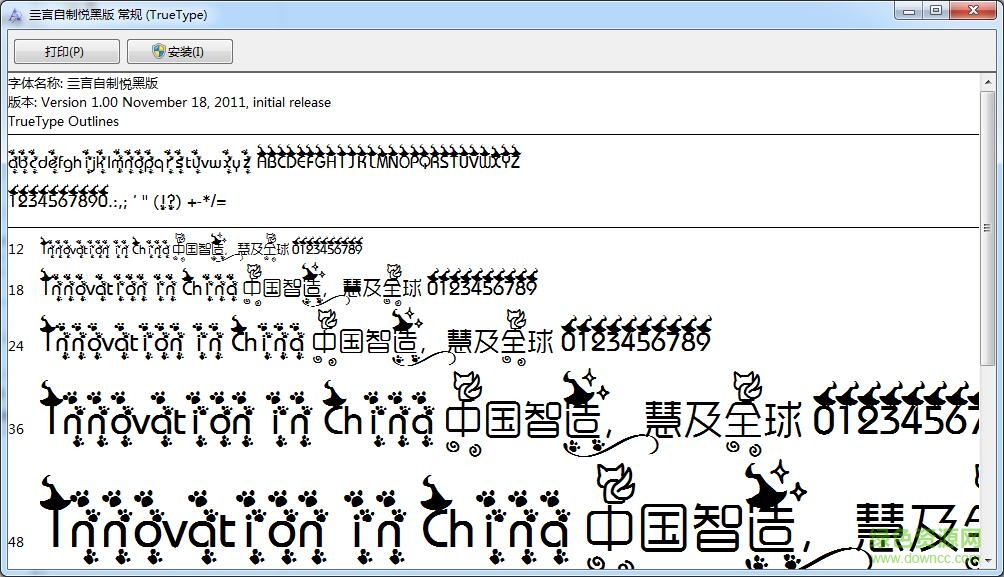
時(shí)光女與貓字體是一款免費(fèi)的貓咪字體。少女心比較強(qiáng)的網(wǎng)友相信你一定會(huì)愛上這款字體的,字體呆萌,不是可愛!算是可愛字體中的一種吧!歡迎網(wǎng)友們下載使用。
時(shí)光女與貓字體是小編比較喜愛的一款字體!這款字體非常有個(gè)性,簡(jiǎn)體的字體通過貓咪爪的點(diǎn)綴變得生動(dòng)起來,在設(shè)計(jì)行業(yè)很受歡迎!